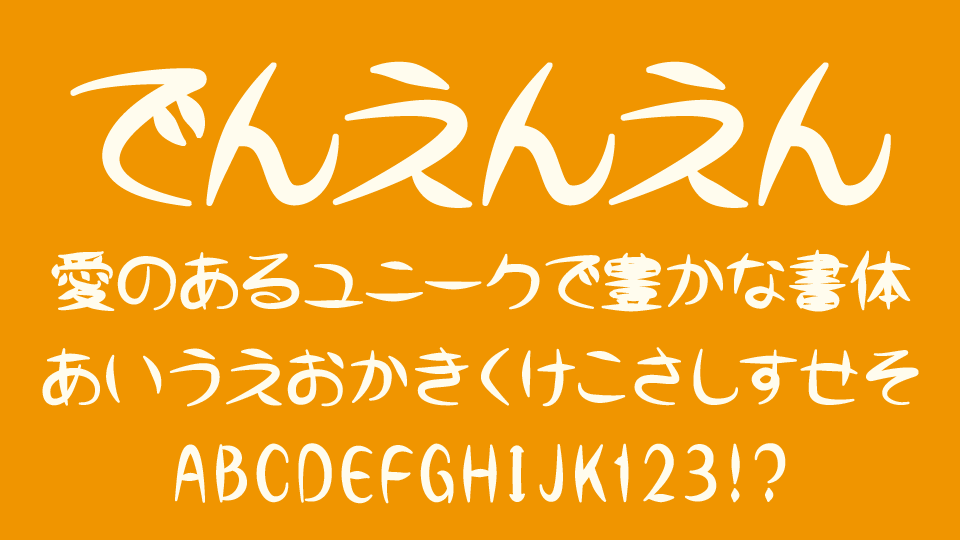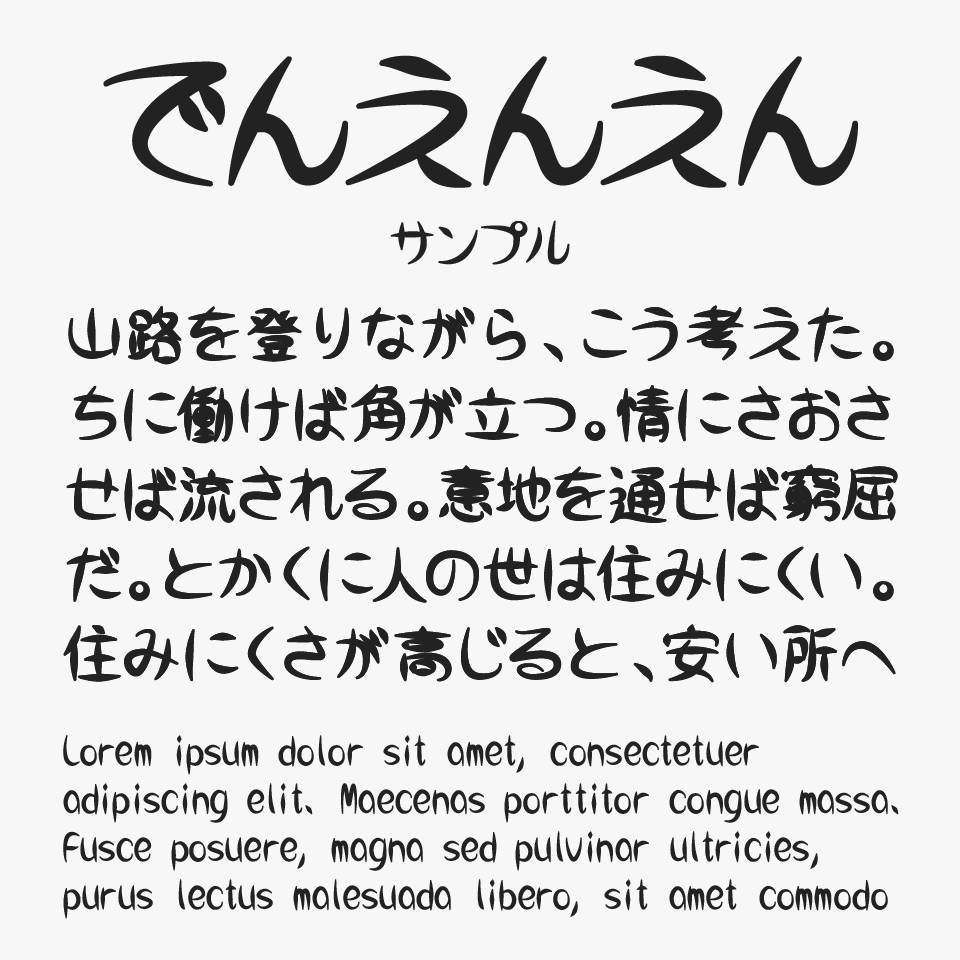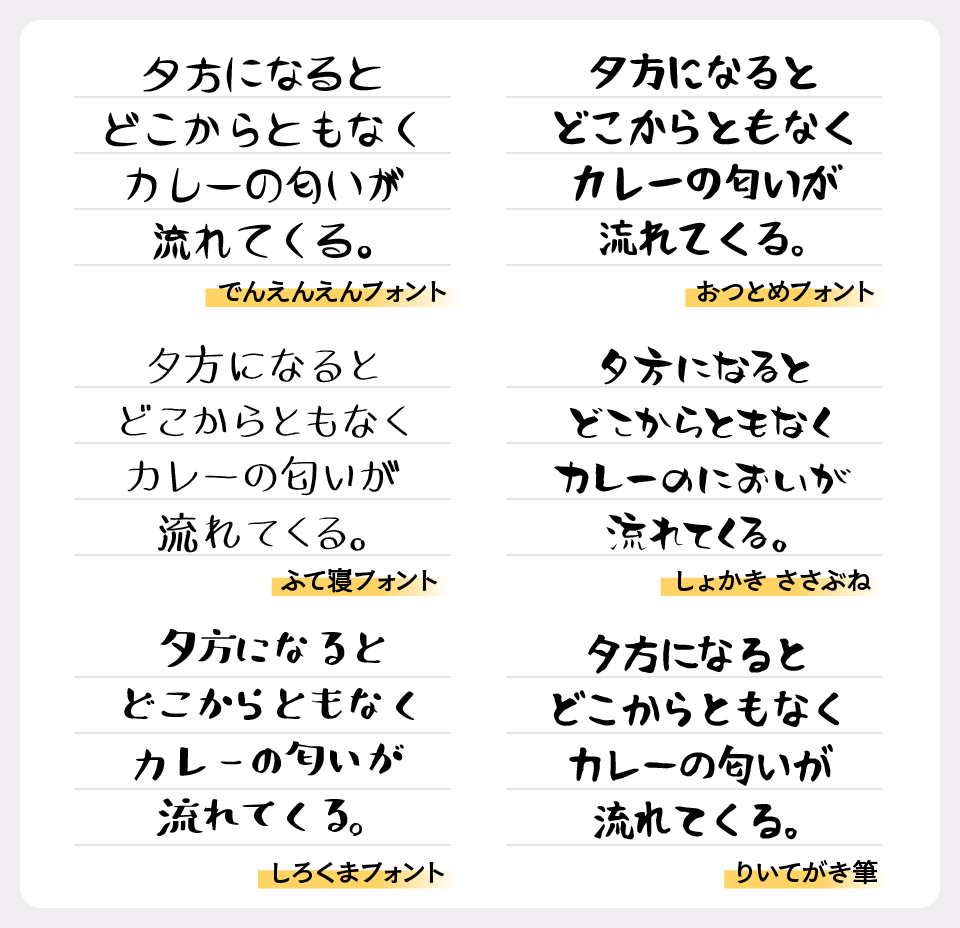
でんえんえん
でんえんえんフォントは、筆で勢いよく描いたようなストロークと、大胆な抑揚が魅力の和風デザインフォントです。
文字の端には鋭いハネやハライが取り入れられており、一文字ごとに強い躍動感とエネルギッシュ感が感じられるフォントです。墨文字のような迫力を持ちながらも、伝統的な筆文字ほど重たくなりすぎず、どこか親しみやすく軽快な雰囲気があるところも特徴です。
和風タイトルや祭りのポスター、ゲームロゴ、映像作品のタイトルなどに使うと相性が良さそうです。また漫画のネガティブっぽいセリフ文字のなどにも良さそうです。太い線と鋭いアクセントによって、短い言葉でも高い存在感を発揮できるため、視線を集めたい場面にもぴったりです。
でんえんえんを、ほかの細身で筆文字風スタイルを持つフォントと比較してみると、力強い筆の勢いと遊び心のある表情が特に際立っています。
比較フォントは、「おつとめフォント」「ふて寝フォント」「しょかき ささぶね」「しろくまフォント」「りいてがき筆」と使用していますが、どれも独自性のある筆文字風あるフォントなので、ぜひあわせてチェックしてみてください。
収録文字は、漢字(6382文字)・ひらがな・カタカナ・アルファベット・数字・記号が収録されています。